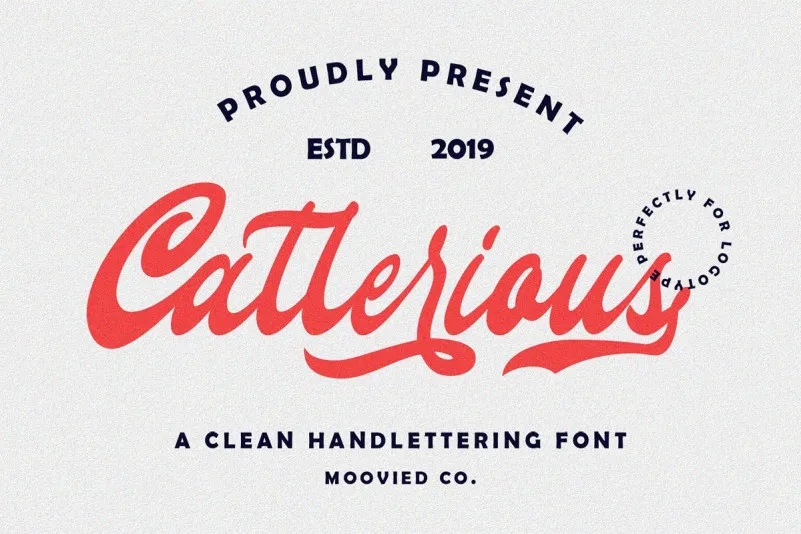
Callerious Script Font – Download Grátis
Através do Callerious Handlettering Font, você pode começar a nova jornada com uma escrita cuidadosamente elaborada. Esta fonte foi criada pela M.0Type para oferecer um estilo de letra que combina elementos urbanos e vintage, inspirado na cultura da rua, em um toque romântico. Ideal para aplicar em diversas finalidades, como rótulos de produtos, logotipos, texturas de marca, gráficos ou até mesmo enfeites para redes sociais. O Callerious Script é perfeito tanto para o design de livros e títulos de capa quanto para eventos especiais. Este estilo elegante é uma excelente escolha para aquelas criações que exigem personalidade e charme, proporcionando um toque único aos seus projetos visuais. Com a Callairus Handlettering Font, você pode não apenas começar o dia com uma nova letra, mas também transformar qualquer projeto em algo realmente especial.